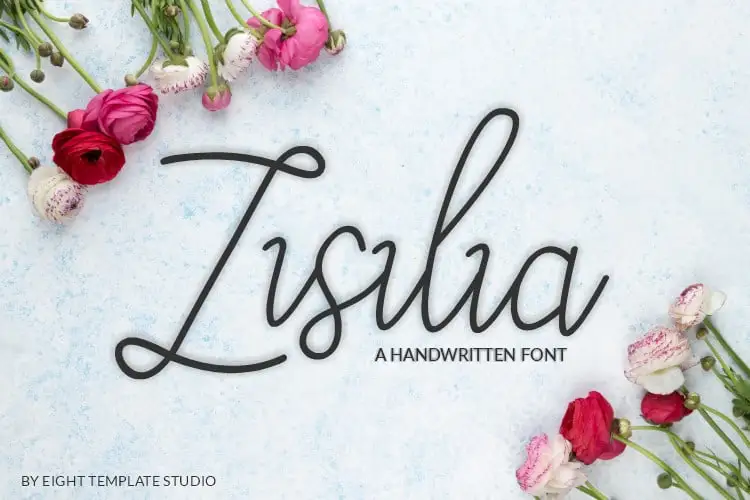
Zisilia Handwritten Font – Download Grátis
A Zisilia Handwritten Font é uma elegante fórmula de letra escrita à mão que combina delicadeza e fluidez ao mesmo tempo. Perfeita tanto para trabalhos profissionais quanto para criações artísticas, esta fonte apresenta caracteres bonitos e equilibrados que se adequam a uma ampla variedade de designs. Seu uso pode transformar seus ideais mais criativos em realidade, iluminando suas concepções e trazendo vida aos seus projetos. Em um mundo cheio de formas digitais, Zisilia oferece algo único e especial. Adquira-a para aprimorar sua estética gráfica e personalizar cada design que faz com que seu trabalho seja notável.